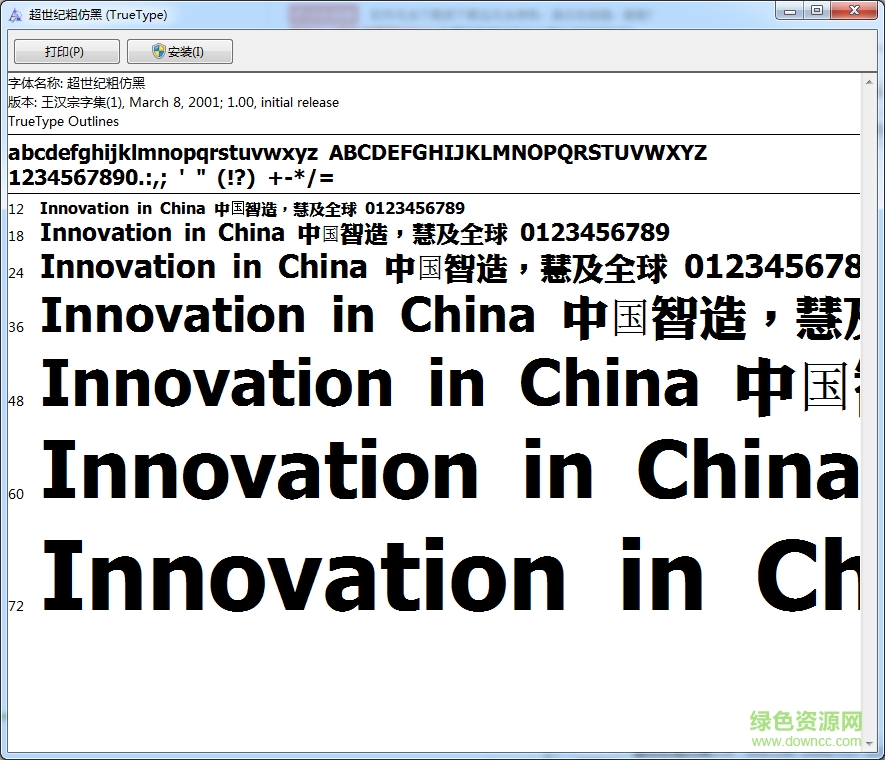
jetlink boldsemiblack 字体
jetlink boldsemiblack 字体又叫超世纪粗仿黑,是一款字型非常粗大的黑体字体,大方得体,干净醒目,便于阅读和识别,也是大多数用户在进行英语文章大篇幅书写的时候所常用的字体之一,非常的方便实用,需要的小伙伴赶紧来绿色资源网下载吧!
jetlink boldsemiblack字体特点
字体刚劲有力,气势雄伟,可应用于文学设计,广告创作、平面设计、印刷包装等领域!